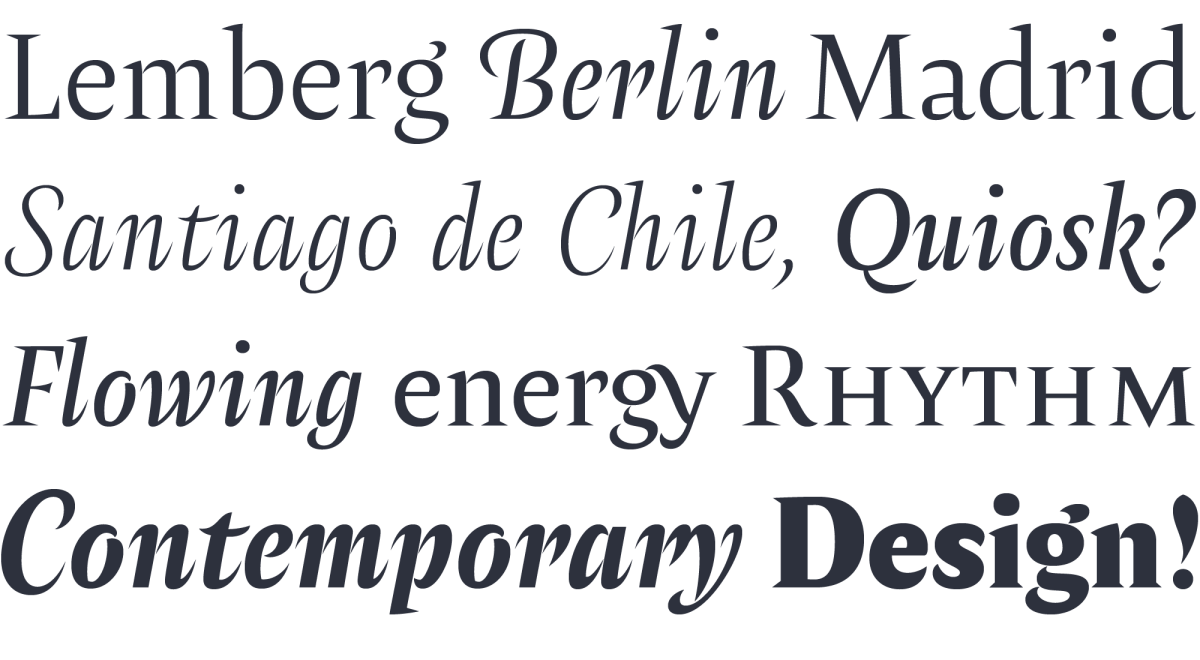
Ya es palabra común entre los amantes del libro que don Mauricio Amster, diseñador de origen polaco, contribuyó seriamente a las artes gráficas de Chile, en particular al libro. Sin mucha certeza de si Amster merece homenajear a Amster y viceversa, o todo lo contrario, de buenas a primeras me resulta prudente que un diseñador (Gálvez) evoque en su trabajo el trabajo de otro diseñador (Amster), así elípticamente, en lugar de zambullirse escandalosamente en el penoso pantano del ego, del que tantos creadores no logran salir. ¿Qué dirían Freud o Lacan? Probablemente se habrían aburrido. Sin contar que ya es raro que un diseñador de letras se sienta el autor de las mismas cuando todos sabemos que el alfabeto lo inventaron los epigrafistas de la Antigua Roma… bueno en rigor lo copiaron del griego, quienes lo heredaron de los fenicios, y parece que no lo inventaron ellos tampoco sino que lo tomaron de pueblos más sabios del Sinaí, con el único propósito de garabatear en sus tablillas de barro los productos que comerciaban por el Mediterráneo: 13 ovejas, 7 cabras, 2 atados de carne seca, 6 puñados de aceitunas verdes. Macerar las aceitunas con abundante orégano y ají rojo en aceite de oliva. Si el cabrito no es muy grande y aun vive dejarlo ir en compañía de su madre y sus hermanos en el monte. Cómase una buena tarta de zapallitos y deje de atormentar a los animales bichitos del Señor. No importa qué palabras se empeñe Ud en escribir, todo lucirá bien si las compone con la tipografía Amster. No se la puede engañar.
Cómo reconocer la dignidad en tipografía
Leo en un comentario sobre este diseño de Gálvez publicado en PampaType en 2015 que las letras tienen “una energía singular”. Es cierto que las curvas de estos caracteres resultan particularmente limpias y las partes negras y las partes blancas de cada signo están como en una tensión armoniosa. Pero de allí a decir que tienen ¿energía? me parece excesivo. Para que las letras tengan energía primero habría que creer que el universo es energía, con el riesgo que eso tendría para todas nuestras creencias. Dejo al lector que ajuste el mundo al tamaño de su mirada. Yo prefiero ponerlo así: los caracteres de Amster tienen una distribución armoniosa de blanco y negro, una relación agradable de forma y contraforma, tienen un ritmo, un swing, una tensión tal que las palabras resultan, además de fácilmente legibles, muy elegantes, y hasta poéticas. Si Ud mira con cuidado verá que una palabra en Amster es como un pequeñito monumento a la palabra. El conjunto del texto exhala dignidad, buen porte, precisión, certeza, cualidades que así combinadas son muy difíciles de encontrar en el vasto universo tipográfico. Lo inconmensurable se vuelve manejable si uno se pone exigente. Y esta tipografía, conviene decirlo, es para gente exigente. Amster es el resultado de un lento maridaje entre tradición y modernidad. Gálvez, costurero abnegado, trabajó durante 7 años en ello. No es nada si se lo compara con la historia del alfabeto, claro. Pero en la vida de un mortal 7 años es mucho tiempo. La tipo Amster ha sido concebida con una mirada fresca de la historia pero desde un ejercicio minucioso del amor por el trabajo y el respeto a las palabras. Respetar las palabras es quizás la clave. Pero ¿quién será este Francisco Gálvez, me pregunto, como para creerse en la libertad de crear un objeto semejante?
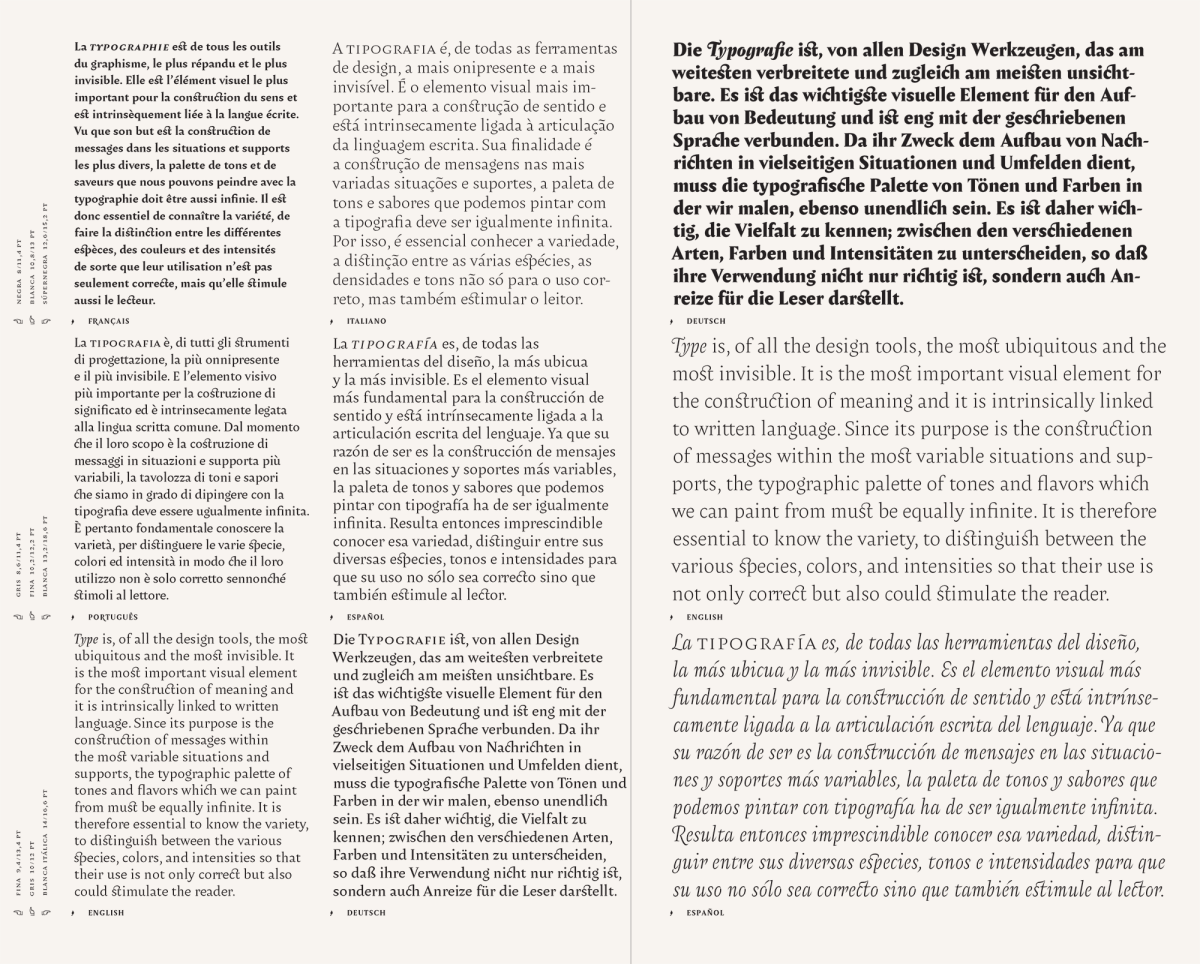
Todo lo que puedo decir de esta tipografía Amster es que todos sus pesos logran un gris muy parejo en los panes de texto. Esto parece ser algo muy importante para los diseñadores editoriales, quienes a menudo confunden una edición con un conjunto de bloquecitos: bloquecitos de texto, bloquecitos de imagen, bloquecitos de blanco, bloquecitos. Te arman una retícula de líneas y módulos, y se pavonean muy orondos de que la geometría rija sus decisiones. Todas. De hecho se los puede reconocer fácilmente en la calle: cuando van a comprar pan a la esquina caminan por la vereda de un modo consistentemente estructural, por ejemplo que los pies no pisen las separaciones entre baldosas, o que los pies pisen siempre baldosas del mismo color, o de la misma línea. Si Ud se encuentra uno en la calle haga caso omiso, no entienden razón. Y si Ud tuviera una peor suerte y se encontrara al mismísimo Francisco Gálvez, por las dudas salga corriendo en la dirección opuesta. Los diseñadores de tipografías no pueden ser gente normal.
De insectos y embutidos
Otro comentario que escuché: “las letras de Amster son como mariposas”. Quiero suponer que se refiere a que pueden volar. Si no, no se. Como la historia del niño que deshojaba mariposas para saber cómo volaban. Todo lo que descubría era que sin alas las mariposas ya no podían volar. De nada servían las advertencias de su abuela: “puedes cazar una mariposa pero no su vuelo” o “si te gustan las mariposas lo mejor es admirarlas” o incluso “basta de tirarle mariposas a los chanchos”… pero en el niño prevalecía el ingenio a la contemplación (o acaso prevalecía su grave sordera) porque pronto acabó con todos los insectos voladores de la región. Ya de grande le dio culpa y, creyendo compensar el daño perpetrado, puso un puesto de choripanes mariposa al pie del cablecarril de Valparaíso. El eslogan ponía “choripanes ligeros como para irse volando”. Ricos los chorizos la verdad.
Pero el tiempo apremia. Debo proseguir con esas Versales Iluminadas que la atormentada imaginación de Gálvez se ha ocupado en dibujar. Qué manera de complicarse la vida, me digo, cuando todo mundo podría usar Helvetica y dejarse de molestar. Le pedí a mi querido amigo Pedro Gutiérrez Muñón que nos regalara alguna rima. Él, que no tiene mucha experiencia en décimas (y en rigor nunca escribió ningún poema pero lo queremos tanto), me regaló estos versos de abajo.
Le pido que ceda ya su resistencia, estimado lector, y se deje convencer, así yo voy redondeando la introducción. Lo invito sin más a que contemplemos juntos estas letras de Amster, que no se ven todos los días, y las disfrutemos mientras estén vivas. Y lo estemos nosotros.
Si las páginas de un libro admiras
y sus detalles iluminan tu alma
deja que tu corazón se abra
a la elegancia noble que estilan.
Si por las iniciales amor cultivas
y en sus detalles lates, floreces
es muy probable que dejes
por una inicial a tu amada
que la Amster Versal Iluminada
super guapísima te mereces.
(Décima de Pedro Gutiérrez Muñón)
Algunos comentarios de la prensa
“Granjeros y animales, curas y demonios, ciudadanos y borrachos, criminales y víctimas, todos danzan juntos en este sorprendente bestiario de letras, ideal para ficción y atmósferas poéticas.” José Luis Escabeche (autor de la novela La sempiterna gotita de sudor, de inminente aparición)
“Esta danza histriónica de personajes evoca el final de “El séptimo sello”, una larga línea de personajes avanza y se pierde en el horizonte: son los muertos que van danzando felices detrás de La Parca. Ya nada puede preocuparlos.”
Quentín Florido (“El marido de la lavandera”, revista de cine, Unquillo, Córdoba, Argentina)
“Historias naturales y sobrenaturales se entretejen sin descanso en un laberinto onírico de la Biblioteca de Babel, hasta producir un no se qué, que te deja un poco mareado.”
Jorge Gutiérrez (El Saltimbanqui, Antofagasta, Chile)
“Un variopinto catálogo de eventos policiales y escenarios costumbristas de otra época, que nos recuerda que la naturaleza humana no ha cambiado un comino”
Ernestina Villoro (“Ocupadísima”, semanario de cultura literaria, artes visuales y backgammon, Puerto Mont, Chile)
Los comienzos siempre más felices que los finales
No se le escapará al lector suspicaz que el instante de comienzo de una lectura coincide con el punto más álgido de nuestras expectativas. La potencialidad de todo lo acontecible es infinita e inabarcable. Todas las cartas están al reverso. Todas las posibilidades son posibles. La promesa de felicidad, es decir la felicidad, es inconfundible. La alegría interior que gana al hambriento cuando se le sirve el suculento plato de comida, al niño cuando está a punto de abrir su regalo, a los enamorados en su primera semana de amor, es la del lector que comienza un nuevo texto. Sin embargo una vez introducido en la historia el relato se encargará de distraerlo con escenarios, personajes, diálogos, combinando imaginación y verosimilitud para convencerlo de su singularidad. Pero como consecuencia de tanto artificio sobrevendrán en la expectativa inevitables rebajas, muchas veces catastróficas. Lo cierto es que hasta que Caperucita no recupera a su abuela, Alicia no despierta de su sueño de maravillas, Pinocho y Yepeto aun están en el estómago del crustáceo y la Cenicienta aun no gana la lotería, a lo máximo que puede aspirar un final es a emparejar la expectativa inicial. Superarla jamás. Casi siempre, o siempre, decepciona, porque nuestras expectativas son siempre altas.
De seguro esto tiene un correlato en alguna verdad inexpugnable de la física: los comienzos son siempre mucho mejores que los finales. Cortázar decía que todo recae, “salimos del barro en busca de la felicidad y la conciencia y los pies limpios” pero en realidad “somos lo más que somos porque nos alteramos”. Constantemente recaemos y nos rehabilitamos. ¿Qué tiene que ver esto con la tipografía? Mucho. Si volvemos a la página: en aquel instante inicial, casi virginal, que es el comienzo de la lectura, entonces promesa fugaz de plenitud entre texto y lector, ¿qué encontramos siempre, indefectiblemente? una letra inicial.